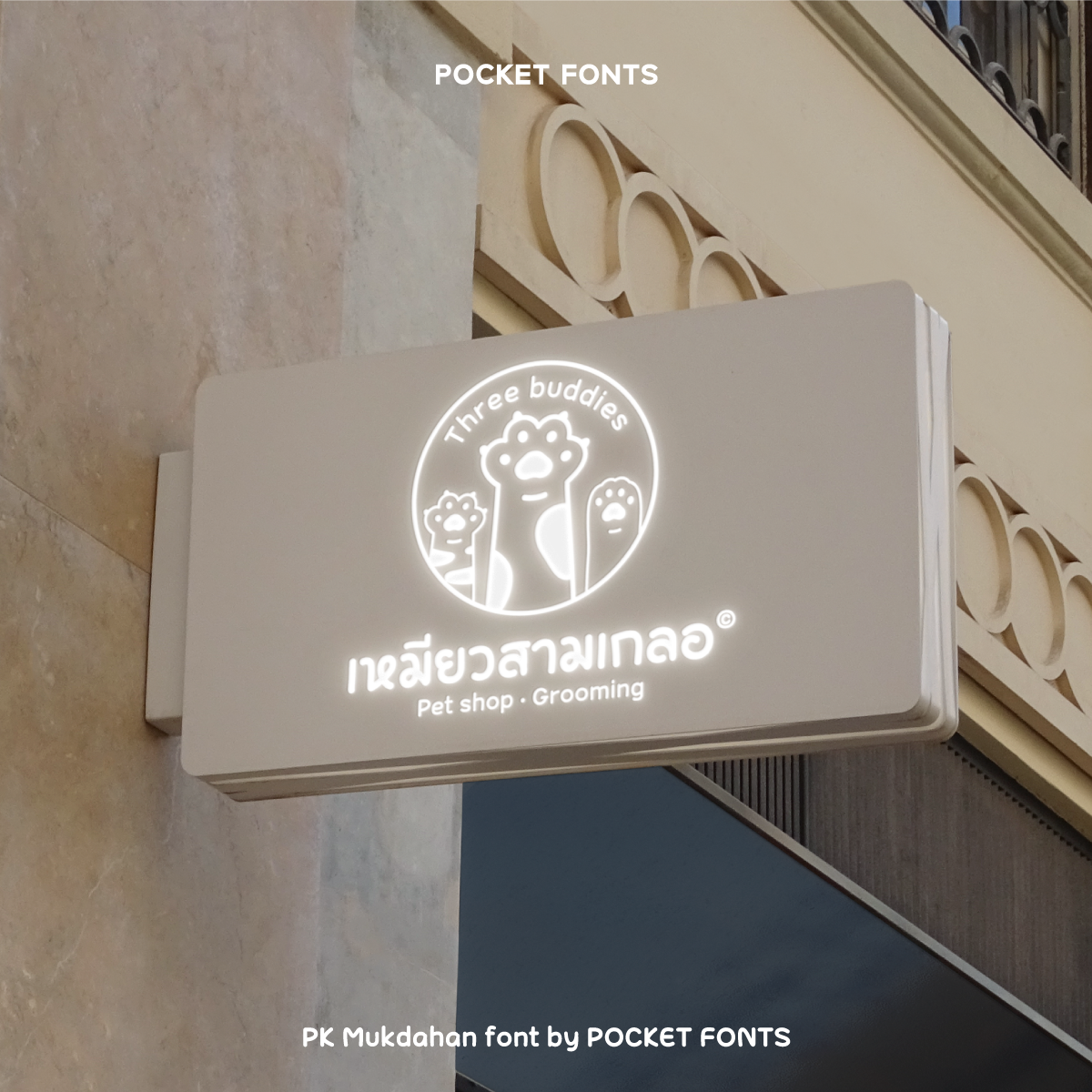
พีเค มุกดาหาร | PK Mukdahan
พีเค มุกดาหาร เป็นฟอนต์ลายมือที่มีทั้งความน่ารักสดใสและมีความหวัดปนอยู่ด้วยแต่ก็หวัดแบบที่ยังอ่านง่ายอยู่ ให้ความรู้สึกเป็นมิตร เป็นกันเองเข้าถึงผู้คนได้ง่าย มี 5 น้ำหนัก Variable ปรับน้ำหนักได้อย่างละเอียดในซอร์ฟแวร์ที่รองรับ